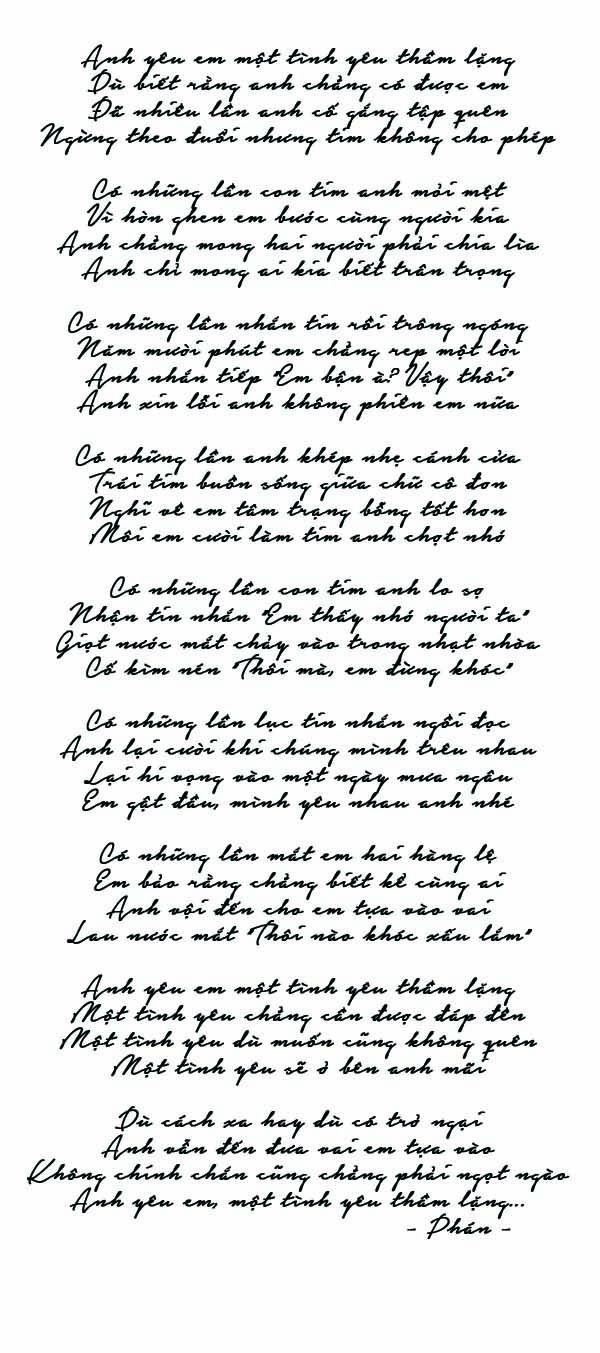
Font chữ viết tay Notera Việt Hóa
Đêm qua trước khi đi ngủ tự nhiên nảy ra ý tưởng là Việt Hóa font mà chẳng biết làm như thế nào ...sáng nay dậy ngồi mò mò :)) ...và đây là font đầu tiên mừn Việt Hóa :D ...mất cả 1 buổi vừa học vừa làm :D
Sau nhiều lần chỉnh lại thì đây là bản hoàn thiện nhất :D
Góp ý sau khi xem pic demo.
Thứ nhất: Độ cao giữa các dấu chưa có trật tự (dấu sắc, dấu huyền quá cao [cái, gì] , sắc trên mũ lại thấp [ế], mũ cao nhưng dấu nặng thấp [ệ, ậ]. Có một số glyphs font nước ngoài có sẵn như â, ê thì thường dấu mũ hơi cao so với chữ (vì font nước ngoài hỗ trợ ngôn ngữ khác, còn với tiếng Việt thì mũ không cao như thế, cái này nên điều chỉnh).
Thứ 2: chữ đen sai, chữ đỏ đúng.
Thứ 3: chưa thấy demo [ư, ơ] nên chưa nhận xét gì thêm. :D
Làm nhiều sẽ lên tay, font đầu tiên mình làm cũng mất 3 tiếng. ;))
Font là hàng rip nên nó viết nhìn có vẻ không được liền mạch như demo gốc nhỉ